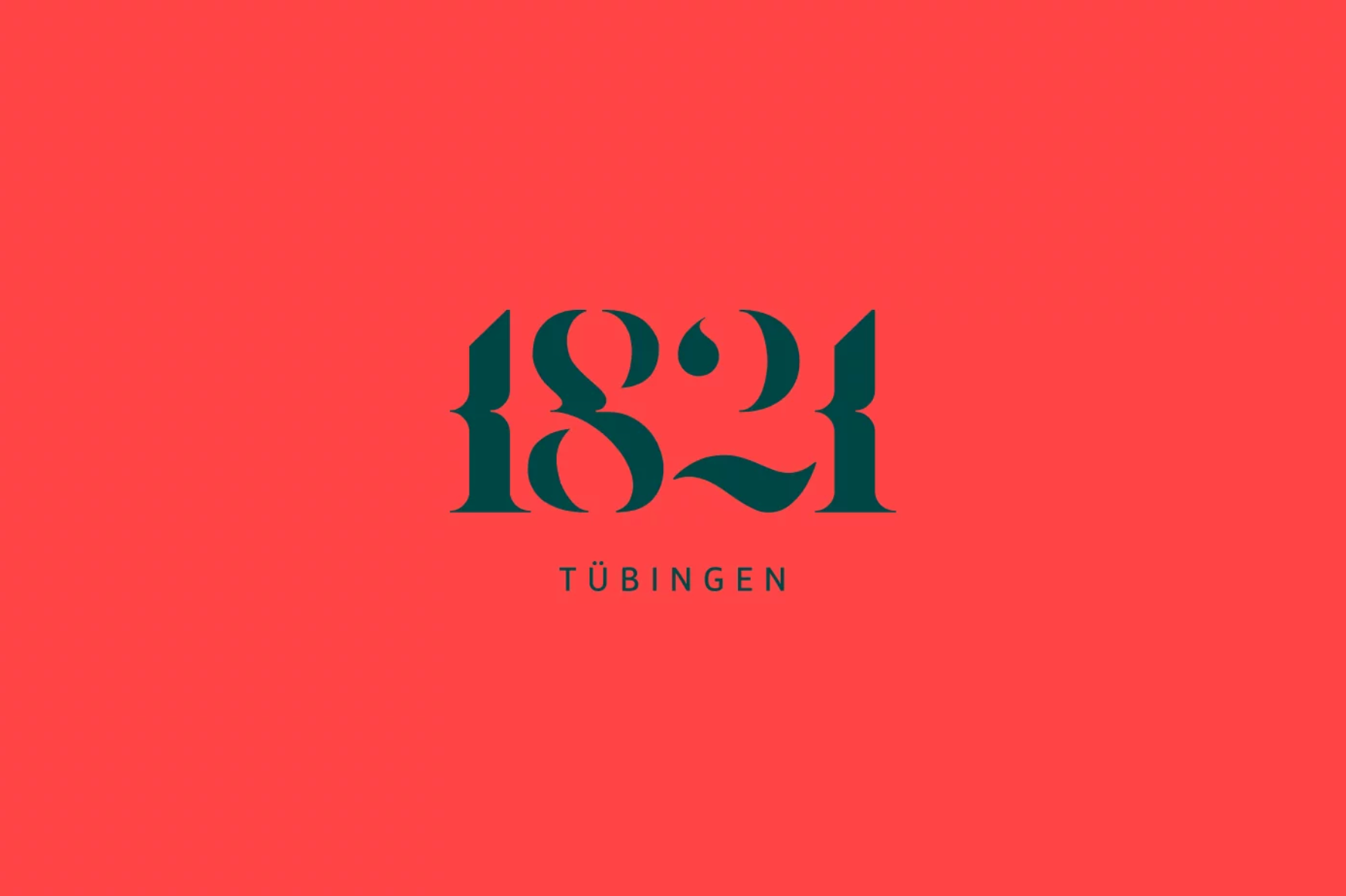
Suche Schrift des Restaurant CI "1821" aus Tübingen
Ich mag die 1821-Schrift. Gerne auch Alternativen, sofern die eine ähnliche Anmutung von Tradition und Moderne gleichzeitig haben.
in der hauseigenen liste wäre die ein vorschlag (obwohl von der anmutung sehr anders). sonst fällt mir da noch die butler stencil ein, die sogar mehrere fettegrade hat. aber natürlich nicht mit dem atraktiven hüftknick deiner ziffern.